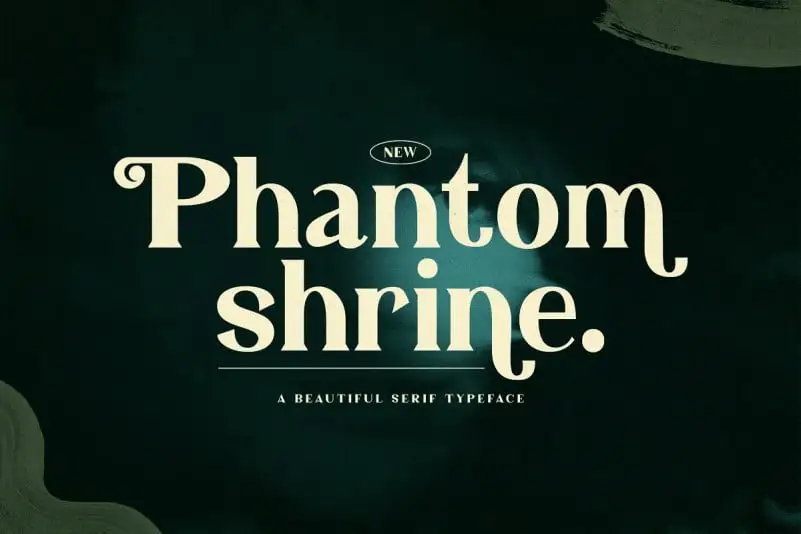
Phantom Shrine Serif Font – Download Grátis
A Phantom Shrine Serif Font é uma escolha inovadora para designers que buscam transmitir elegância em seus projetos. Manufacturada pela StringLabs, esta serif font apresenta um estilo moderno e sofisticado, criando um impacto imediato nos olhos de quem a vê. Ela se destaca como uma opção ideal tanto para textos informativos quanto para trabalhos visuais de alto nível. Com seu design fluido e arquitetado para ser facilmente personalizado com diversos projetos, o Phantom Shrine Serif Font é perfeito para aqueles que desejam destacar suas idéias criativas. Seu charme instantâneo faz com que seus trabalhos se destaquem no mercado, tornando-o uma escolha inteligente para quem busca elegância e sofisticação em cada projeto. Combinada à sua versatilidade, a Phantom Shrine Serif Font transforma qualquer ideia num projeto de primeira linha.